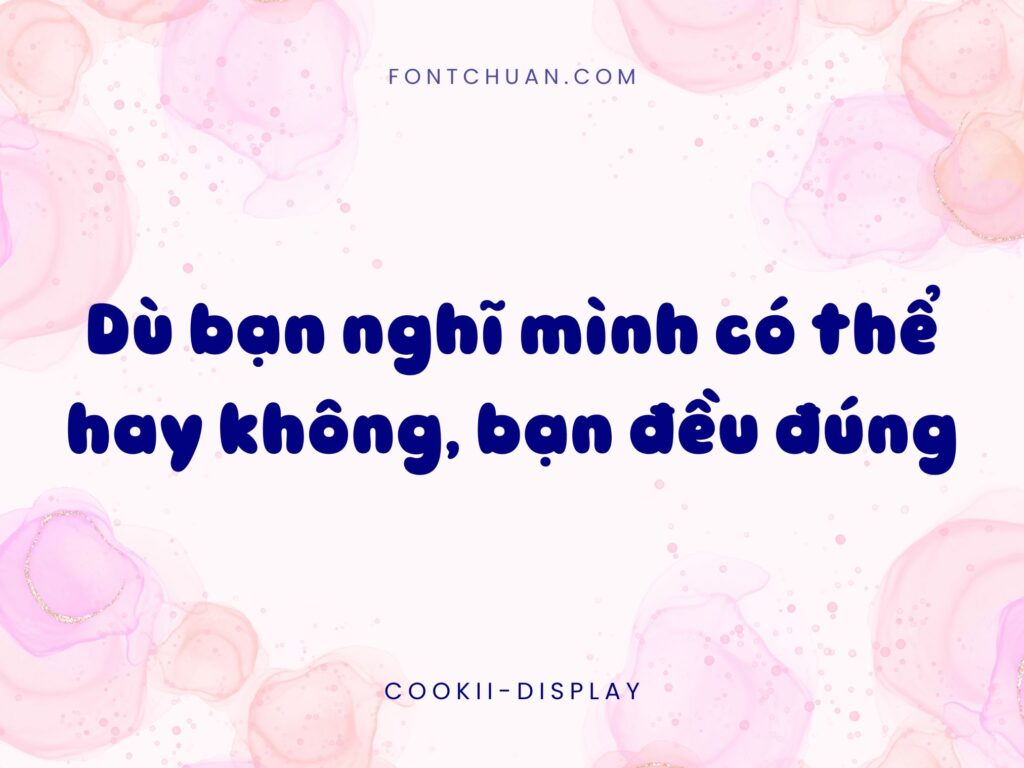
Font Cookii Font Tiếng Việt
Cookii Display là một phông chữ hiển thị đậm và vui tươi, được thiết kế bởi Meo Mii. Phông chữ này mang lại cảm giác trẻ trung và linh hoạt, phù hợp cho nhiều dự án thiết kế khác nhau như thương hiệu sản phẩm thực phẩm, tiêu đề hiển thị, sách thiếu nhi hoặc truyện tranh. Với sự hỗ trợ đa ngôn ngữ Latin, Cookii Display giúp người dùng dễ dàng áp dụng vào các thiết kế quốc tế. Phông chữ này miễn phí cho cả mục đích sử dụng cá nhân và thương mại, giúp người dùng linh hoạt trong việc áp dụng vào các dự án khác nhau
Đặc biệt, Cookii Display có thể được ứng dụng như một Font chữ ẩm thực, giúp các nhà hàng, quán ăn hay thương hiệu thực phẩm tạo sự gần gũi, vui nhộn và nổi bật trên bao bì, menu hay biển hiệu. Đồng thời, font này cũng rất thích hợp làm Font chữ thiệp cưới, mang đến vẻ trẻ trung, vui tươi và hiện đại cho các thiết kế thiệp mời, lời chúc và các ấn phẩm liên quan. Nhờ sự linh hoạt và đa dụng, Cookii Display trở thành lựa chọn tuyệt vời cho cả các dự án thương mại lẫn cá nhân.